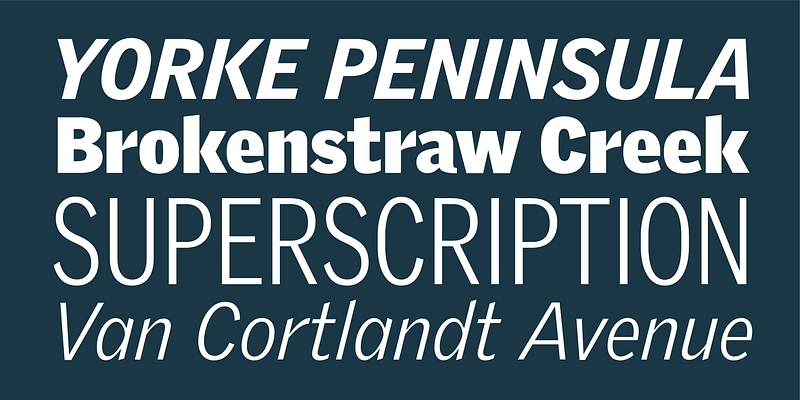
Bell Gothic wurde 1937 von Chauncey Griffith für die Verwendung in Telefonbüchern entworfen und hat sich für deren Schriftgrade bewährt. Griffith Gothic belebt und erweitert das Design für die Verwendung in Überschriften wie auch im Fließtext, indem es mehrere Schriftstärken sowie einige kursive und schmale Schriftschnitte hinzufügt. Die dramatische Ausdünnung der Fugen, die ursprünglich dazu gedacht war, Tintenüberfüllung vorwegzunehmen, wird als ausdrucksstarkes Merkmal fortgesetzt.